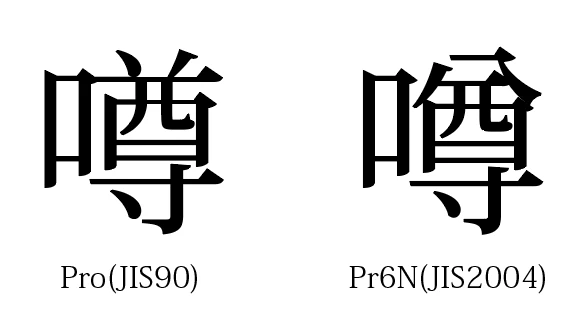
フォント置換すると正体が反映されない
正体で書いているテキストを流し込んだ後フォントを変換するとどうしても正体ではなくなってしまいます。
このような状況を改善する方法はありますか?
例えば、ワードなどでいただいたテキストで「噂」という文字があったとして、コピー&ペースト、ファイル>配置など、私が知っているどの方法を取っても正体ではなく包摂字形になります…。正字のまま流し込みたいので、毎回変わってしまって困っています。
使用しているバージョンはCC2017です。
その原因はInDesignではなくフォント側にあります。
お使いのフォントがStd/Pro/Pr5/Pr6のどれかでしたら、Nが付いたStdN/ProN/Pr5N/Pr6Nにしてください。
monokanoさんの仰る通りですけど、実際の字形として下記になります。
例として使っているフォントは小塚明朝 Pro Rと小塚明朝 Pr6N Rです。
またWindowsの場合はVista以降からは標準がJIS2004準拠の字形になっています。
あわせてですが、CC 2017でも、デフォルトフォントは小塚のPr6Nだとは思いますから、
その時点ではJIS2004に準拠しての表示になるはずです。
あとは今回利用しているフォントが何か、というのはあります。
フォントによってはJIS90のみということもありますから、その場合には対応できない場合があります。
monokanoさんが仰ってるのはOpenTypeフォントの種類としての話ではあるのですが、
すべてがNつきのJIS2004準拠ではないですし、TrueTypeの場合ではJIS90のみやJIS2004のみということもありえます。
その原因はInDesignではなくフォント側にあります。
お使いのフォントがStd/Pro/Pr5/Pr6のどれかでしたら、Nが付いたStdN/ProN/Pr5N/Pr6Nにしてください。